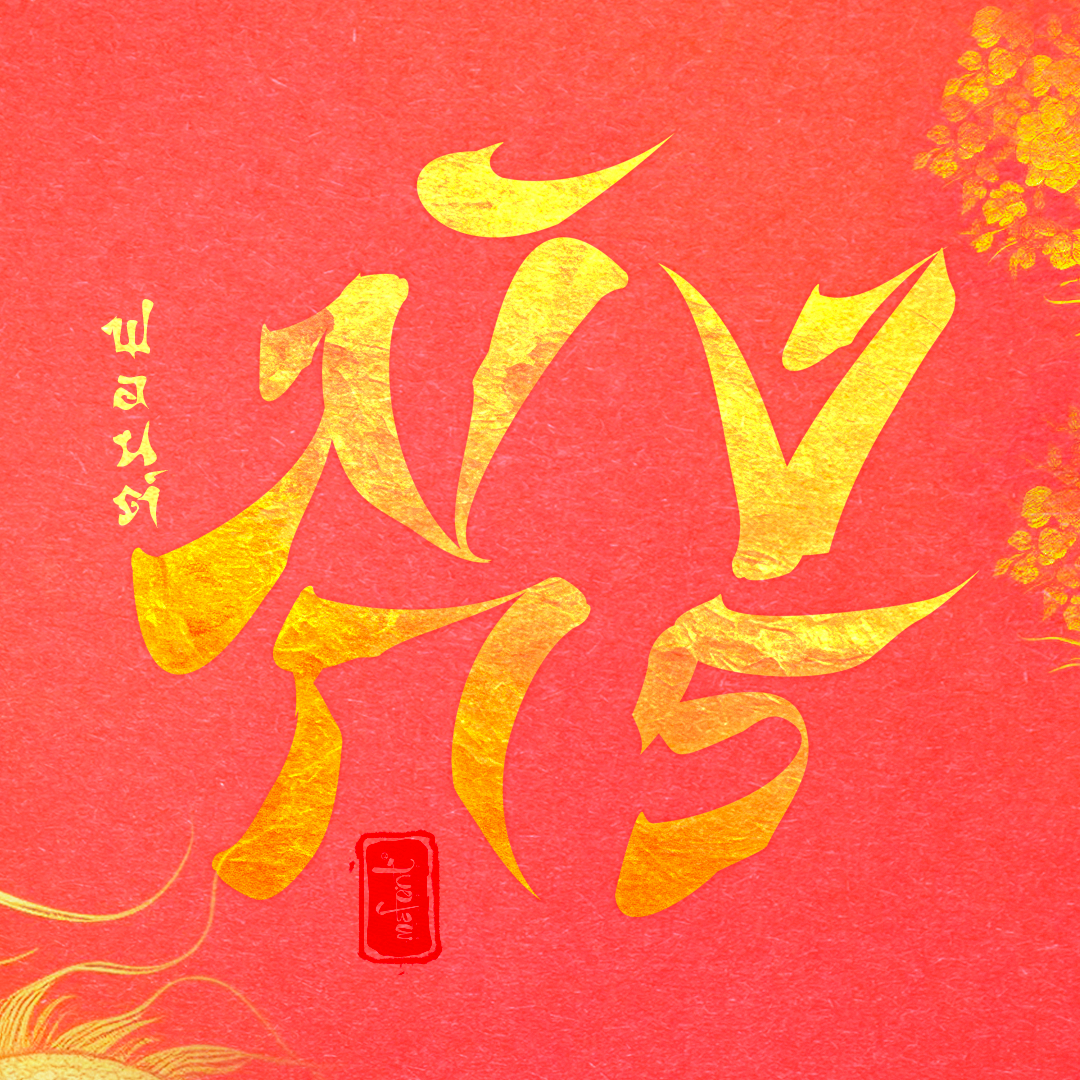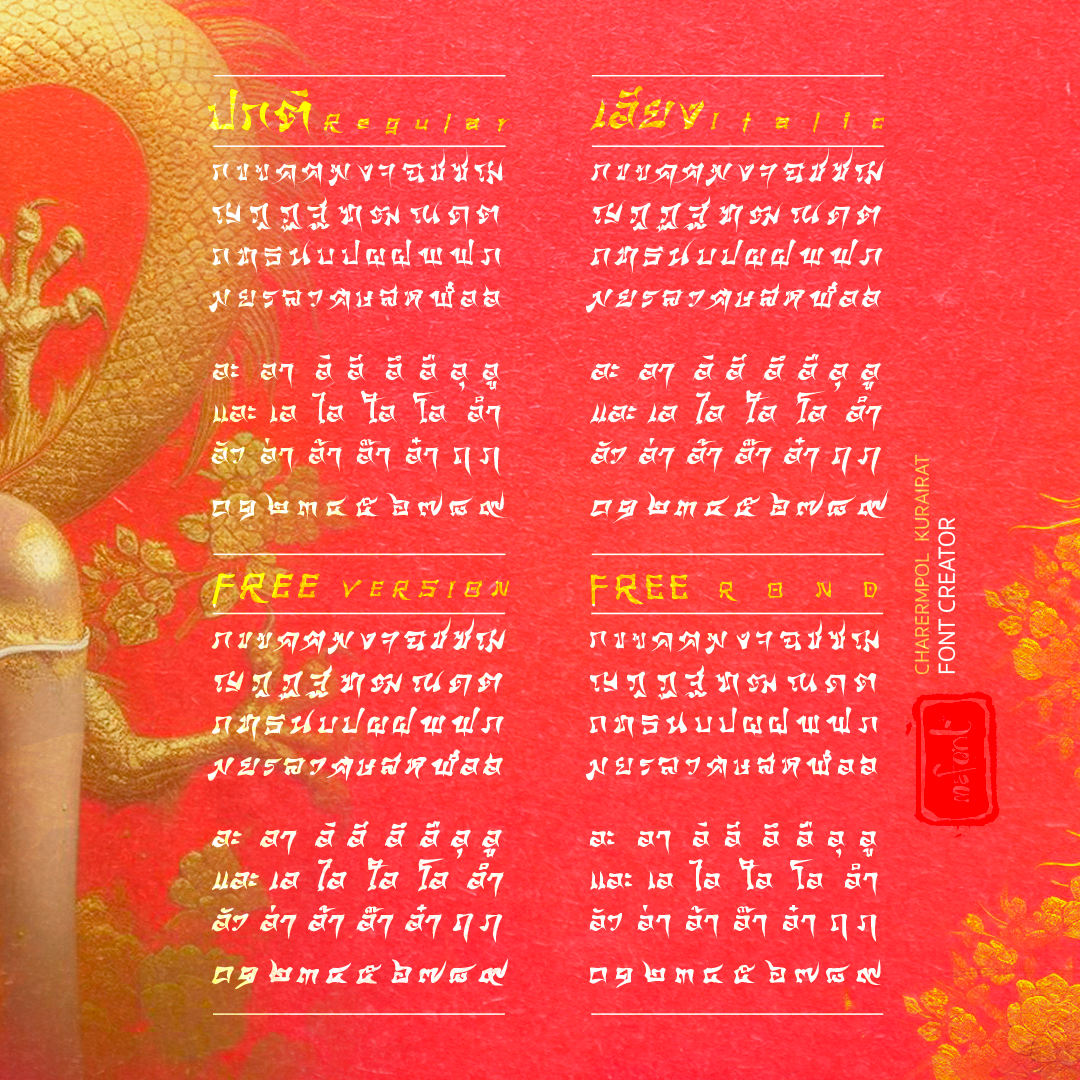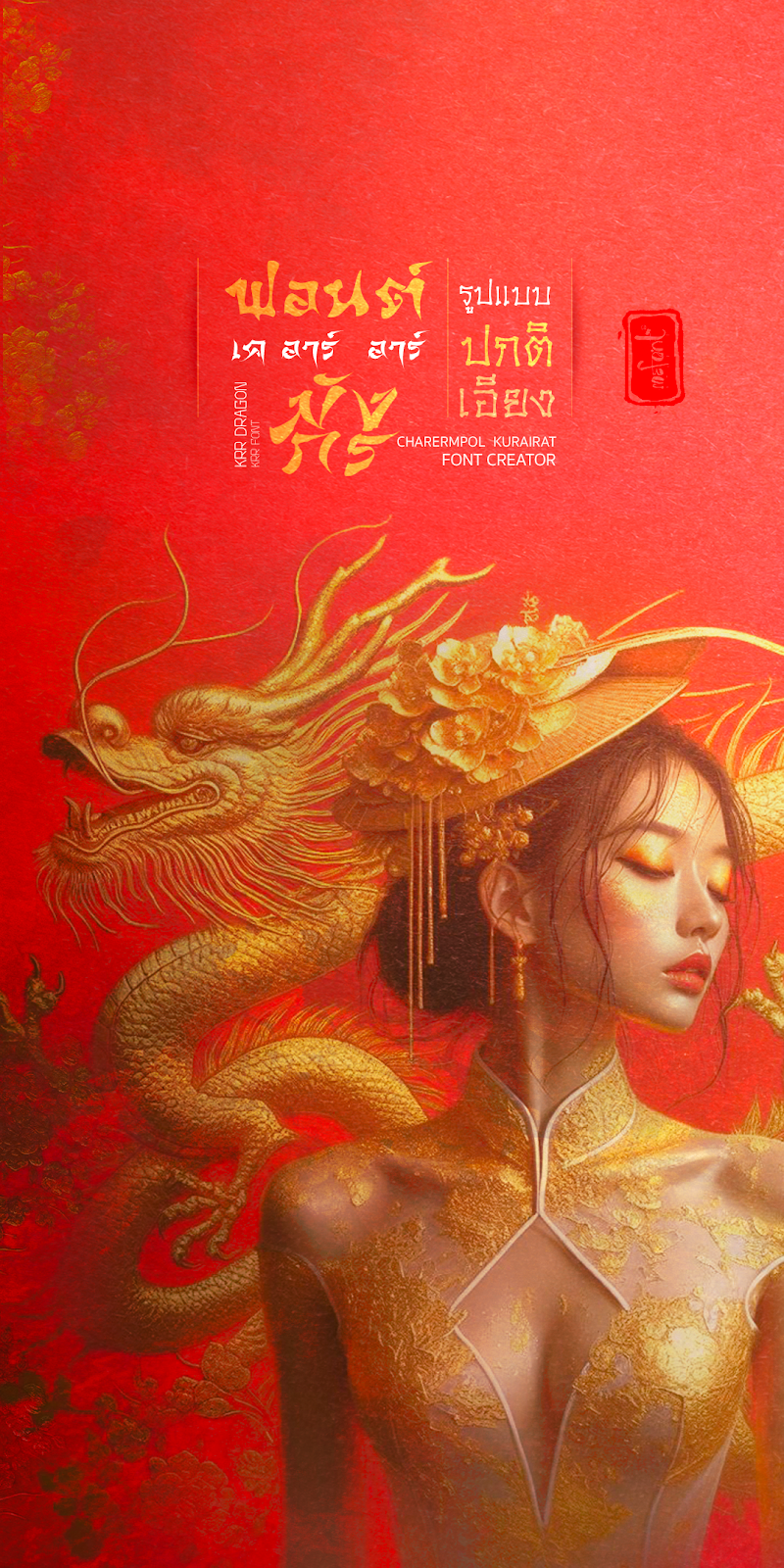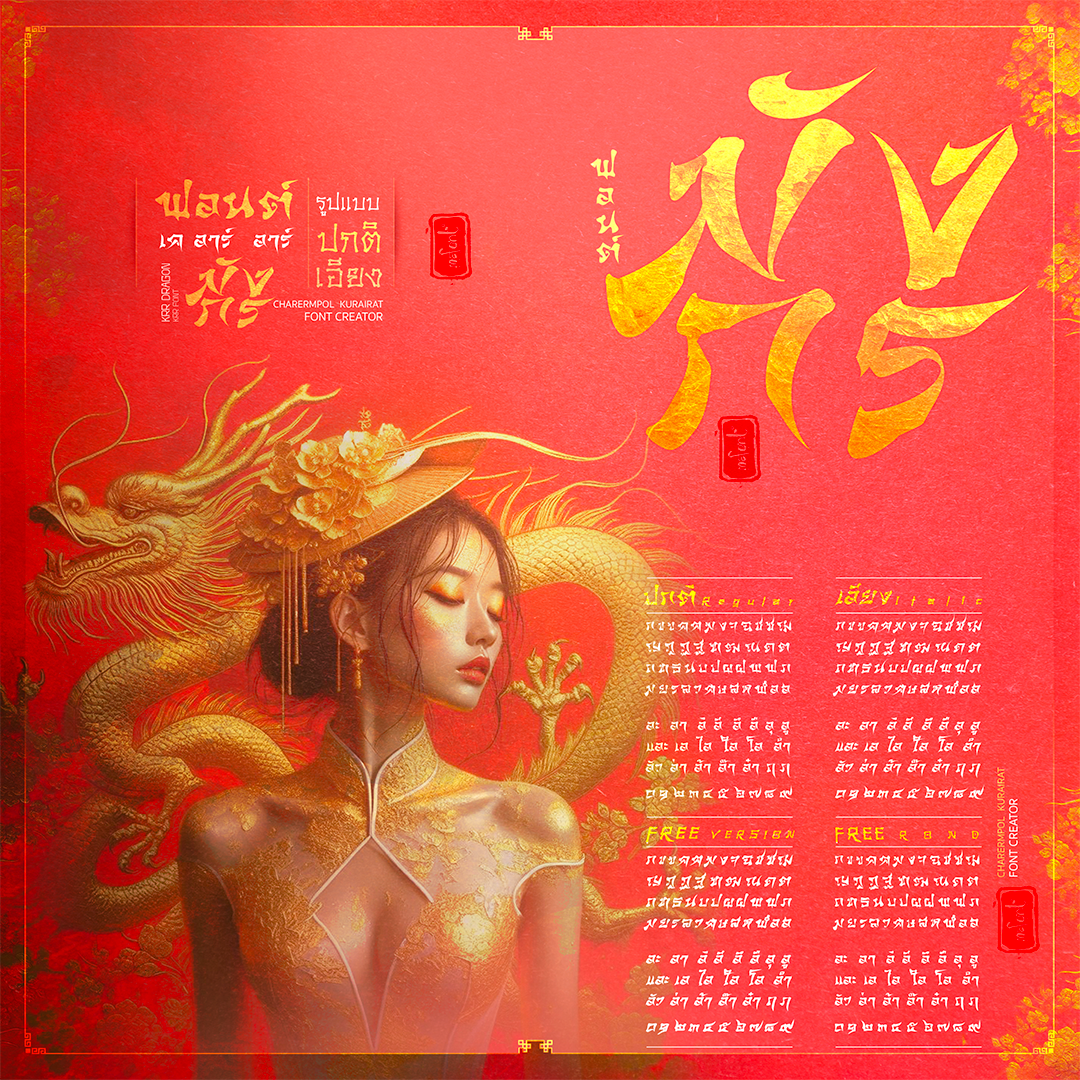
KRR DRAGON (ฟอนต์ มังกร)
KRR  DRAGON (ฟอนต์ มังกร) ยังวนๆเวียนกับรูปแบบฟอนต์จีน
ด้วยความที่หลงไหลชอบแนวจีนๆ ก็เลยสร้างออกมาสักรูปแบบไว้ใช้งานชะหน่อย
ฟอนต์มีสองภาษา ไทย- อังกฤษ  รูปแบบ ตัวปกติ-เอียง-ปลายมน(ฟรีใช้สำหรับส่วนตัว) ใช้ได้ MAC / PC